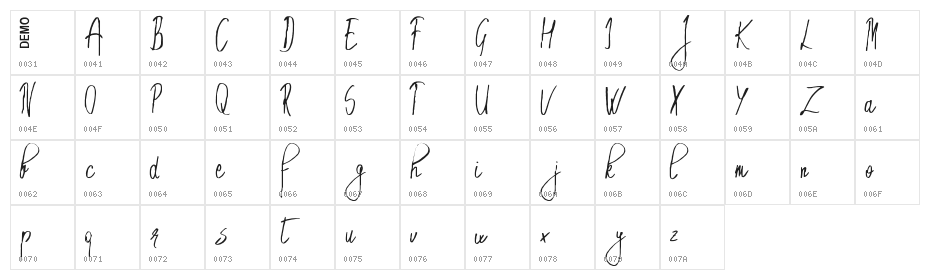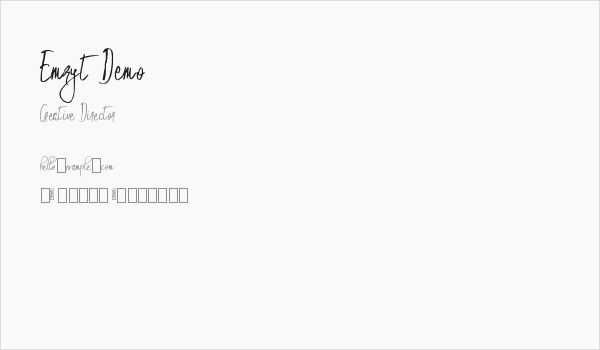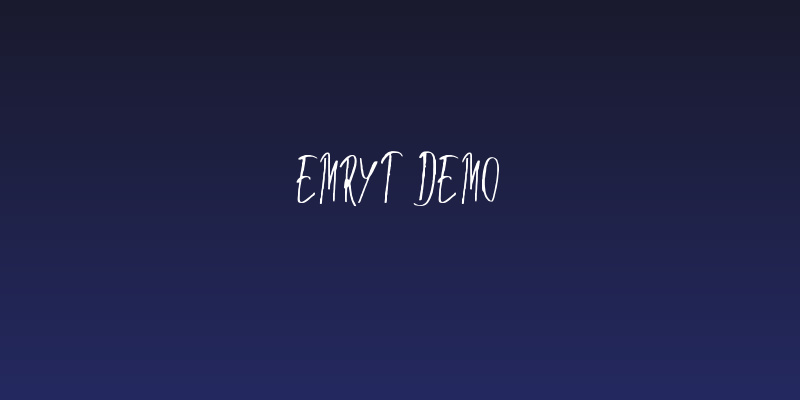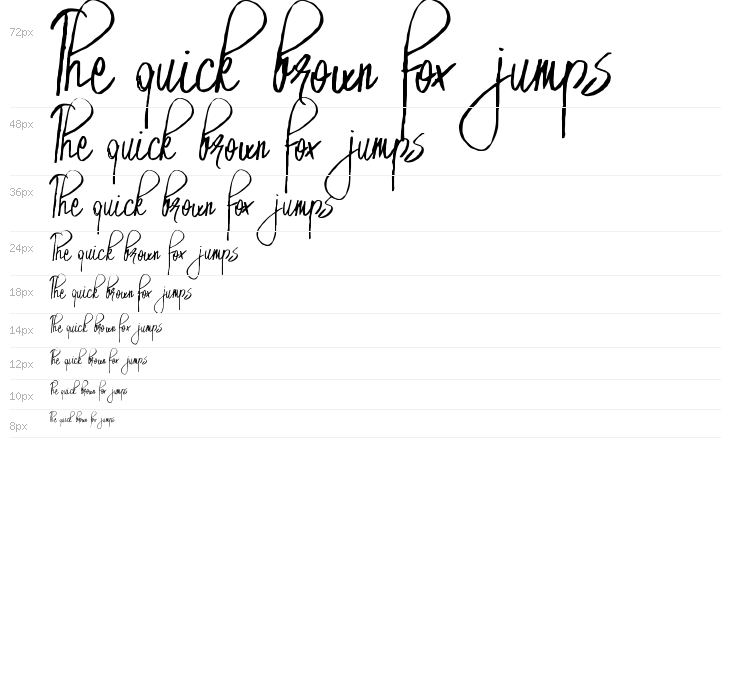
Emryt Demo Font
| Caso d'uso | Logos, Headlines, Artistic projects |
| Progetti proposti | Ideal for creative projects such as invitations, greeting cards, artistic posters, and branding materials that require a personal touch. |